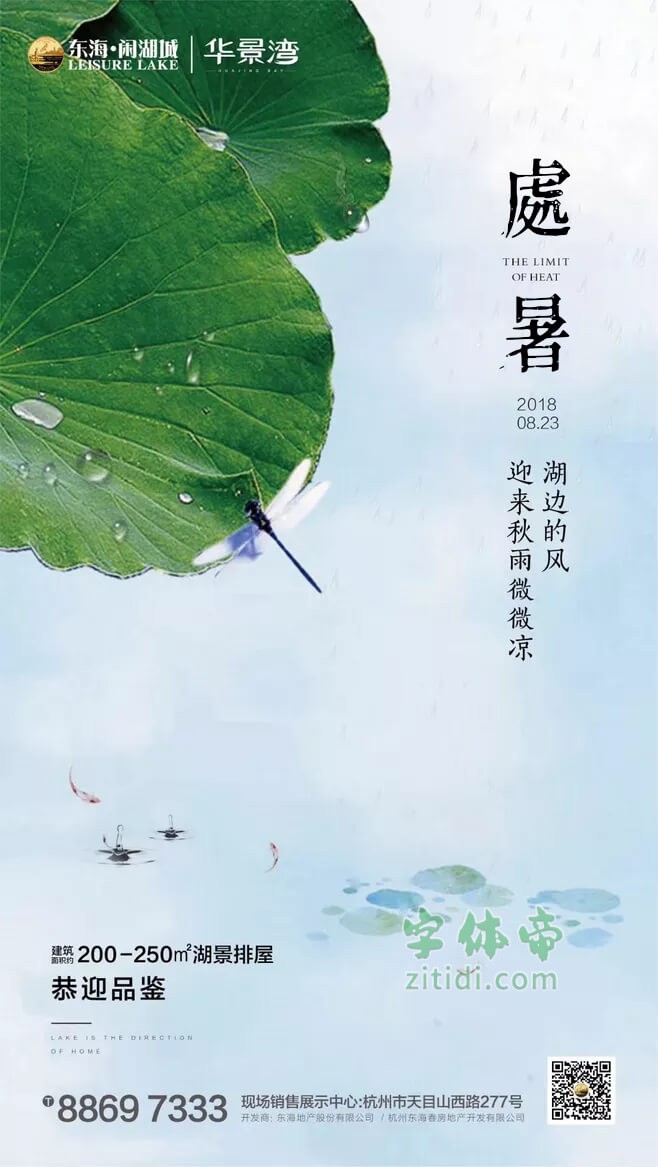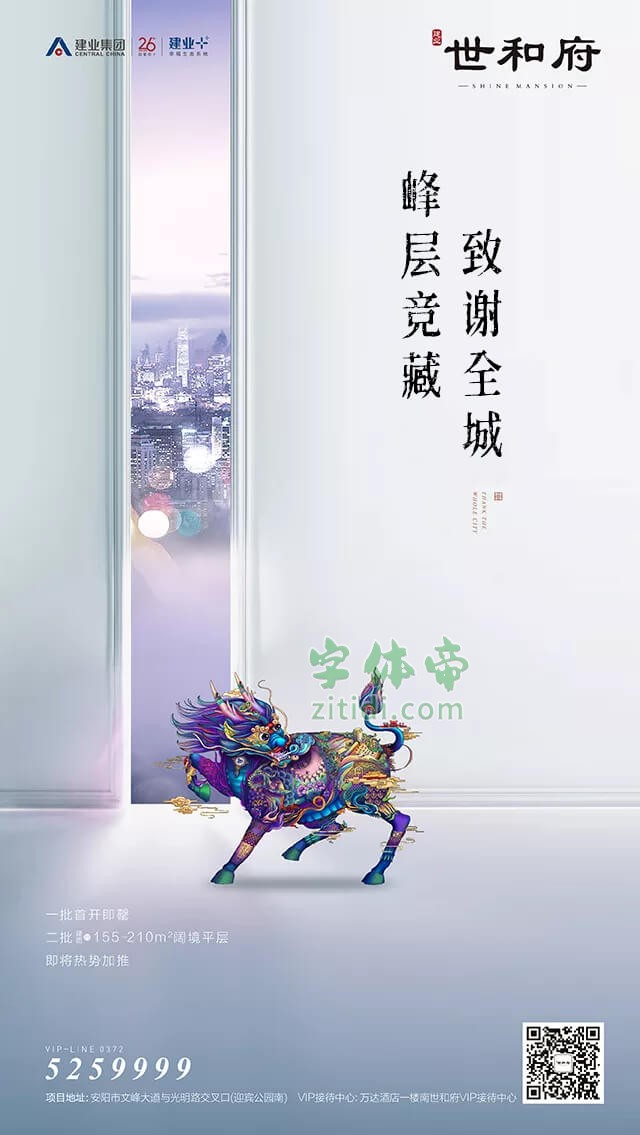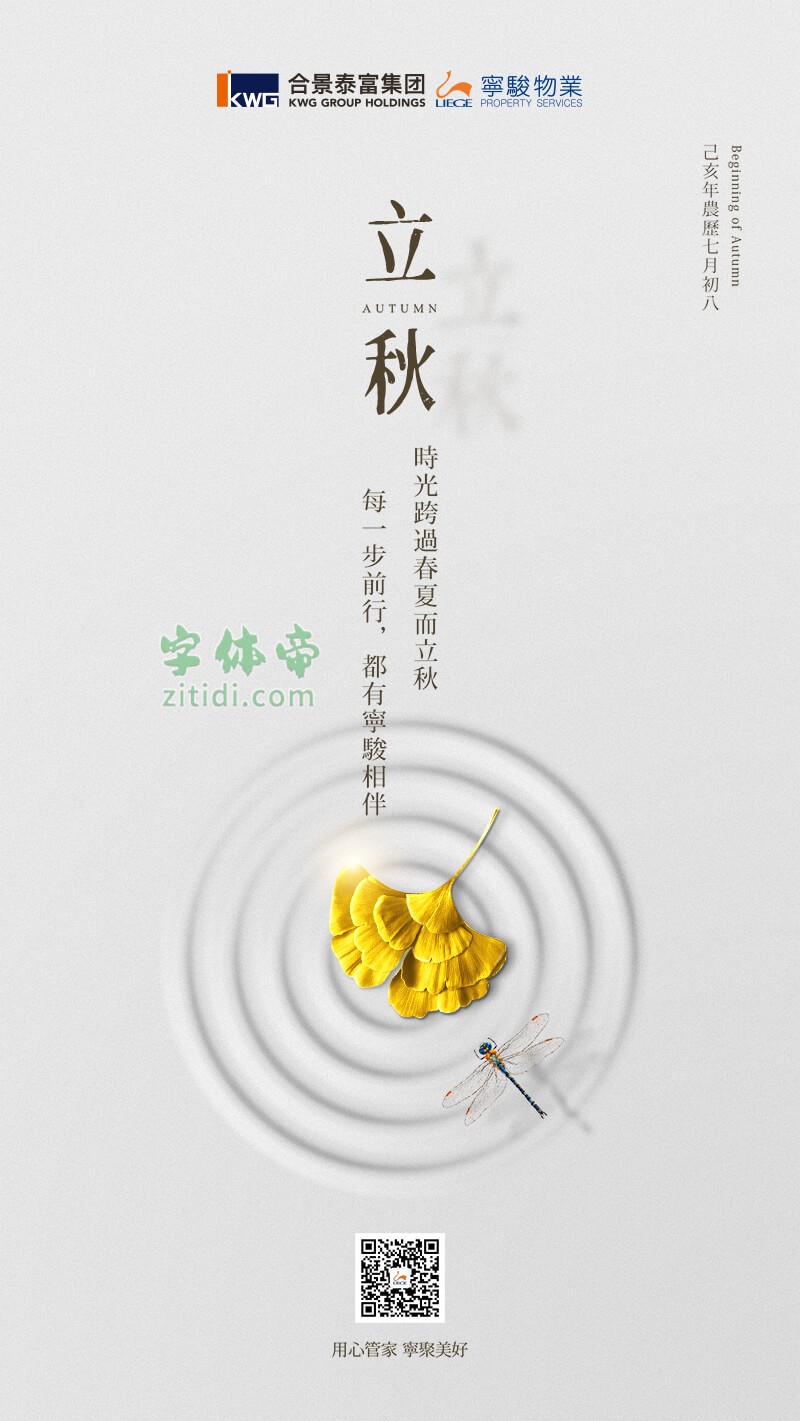
现在隆重推介黄令东齐伋体,一款可以媲美康熙字典体的免费商用字体!可以免费商用!可以免费商用!黄令东齐伋体摘自明代木版印刷书籍《凌閔刻本》,采用半自动计算机视觉和OCR制作而成的一款字体。其笔画风格书法特征浓郁,比常规的明朝体更具韵律感,富有人文气息。黄令东齐伋体非常适宜用于需要展现人文感、手作感、古拙感的场景。
黄令东齐伋体是基本思源宋体改造而来,所以对中文汉字支持极佳,无论是简体还是繁体都基本上不缺字! 如果想使用古籍字形,请使用黄令东齐伋复刻体,十分漂亮的古籍字体!
“黄令东齐伋体”是一款书写很新颖的字体,字体大方,适合各种设计作品使用!欢迎下载!